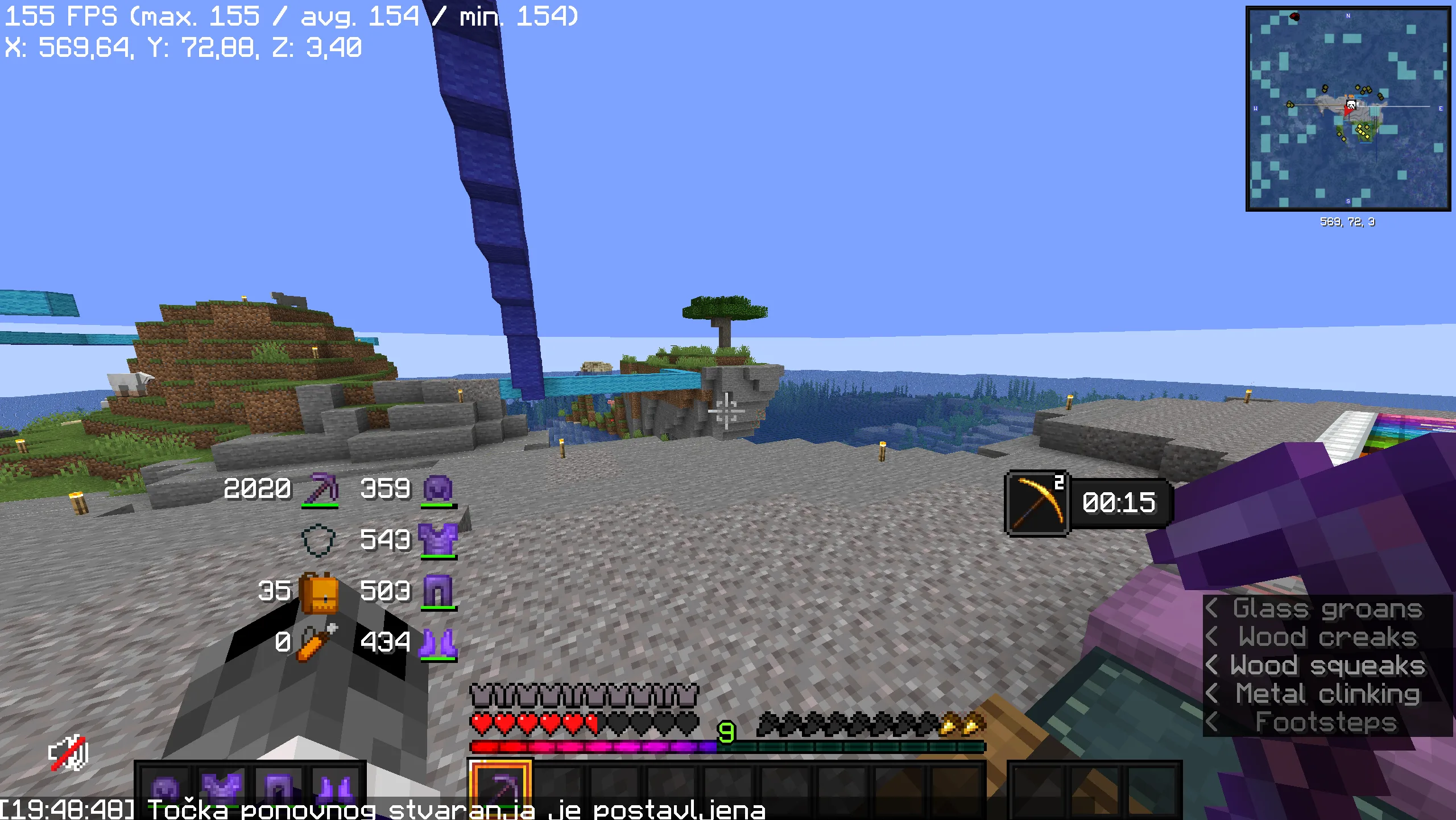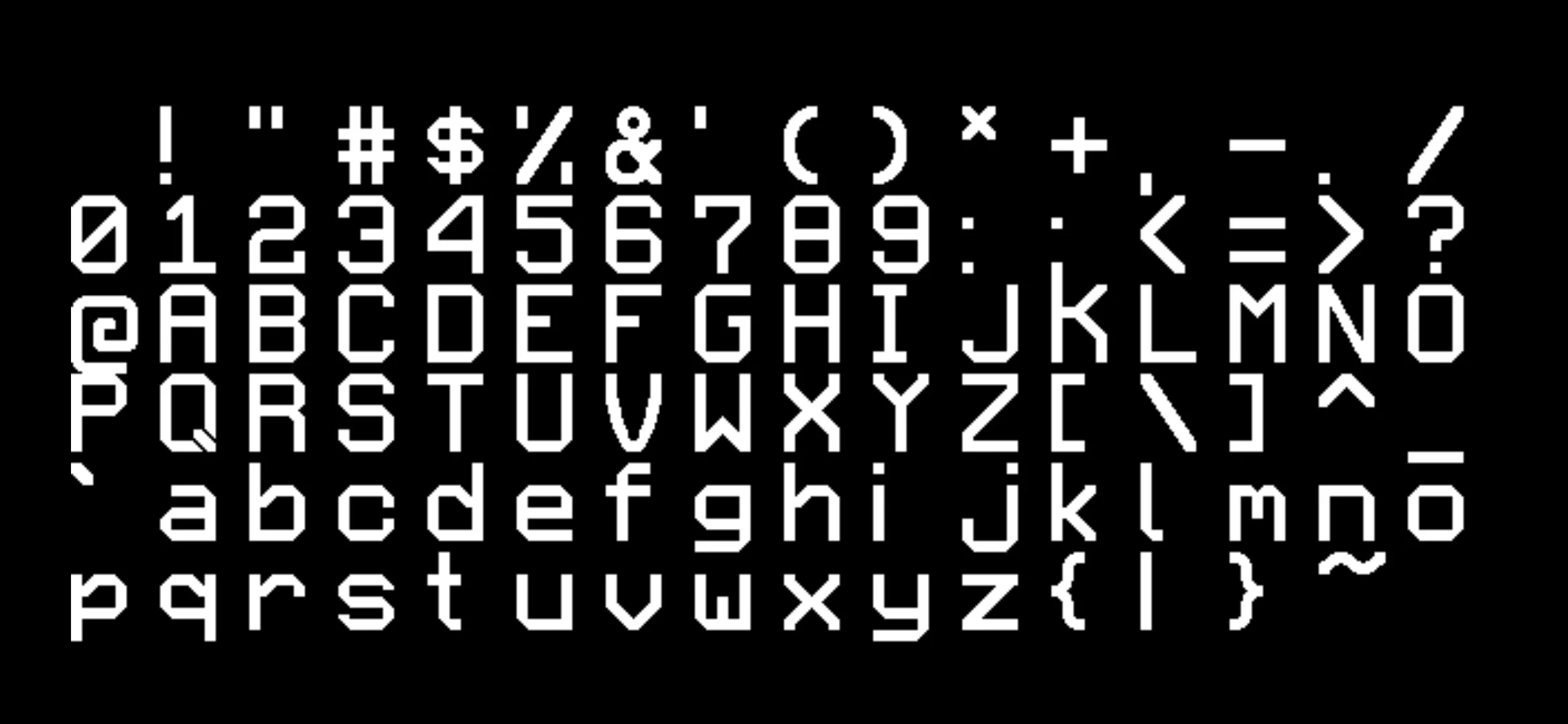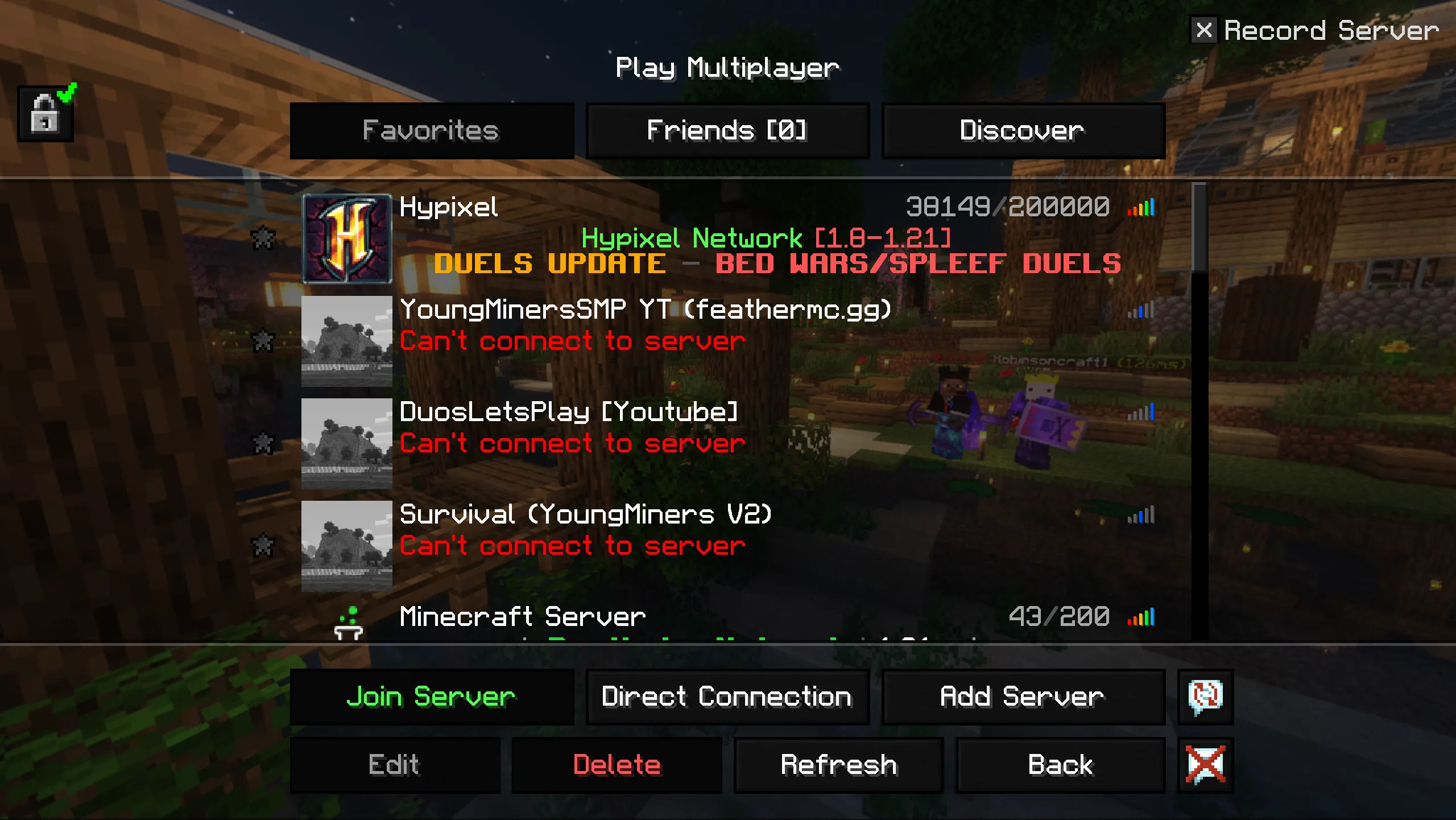
Sharp Fonts [Scale 4x] (GUI Scale dependant)
Этот ресурспак добавляет чёткий шрифт в стиле PVP-паков, который выглядит векторным на экране. Он поддерживает все версии Unicode и доступен в нескольких разрешениях для разных масштабов интерфейса.
Ресурспак Sharp Fonts [Scale 4x] предлагает пользовательский шрифт, который отличается повышенной чёткостью и плавными диагоналями, создавая впечатление векторной графики без пикселизации. Он разработан в стиле PVP-паков и поддерживает все буквы Unicode, обеспечивая универсальность для различных языков.
Пакет доступен в нескольких разрешениях (например, 32x, 48x, 64x, 80x), которые соответствуют разным масштабам интерфейса Minecraft (GUI Scale). Это помогает избежать нежелательных артефактов интерполяции и сохранить резкость изображения. Для масштаба 4x рекомендуется использовать версию 64x для максимальной чёткости.